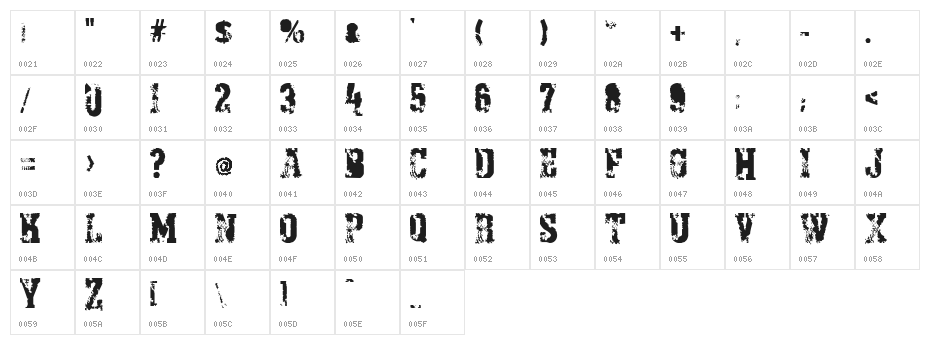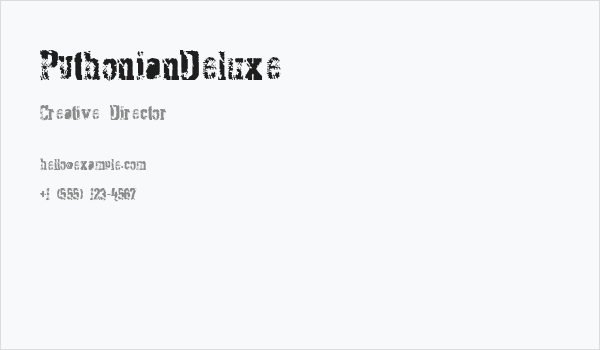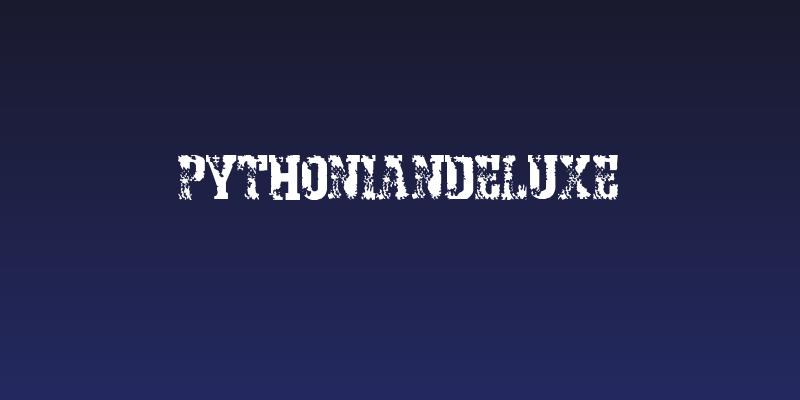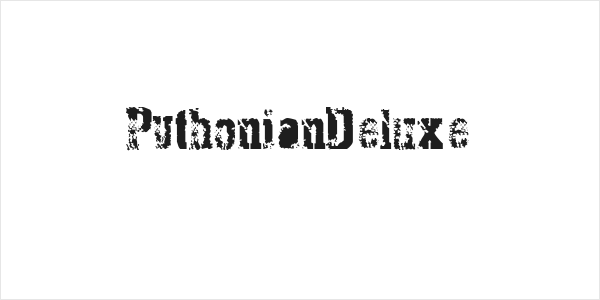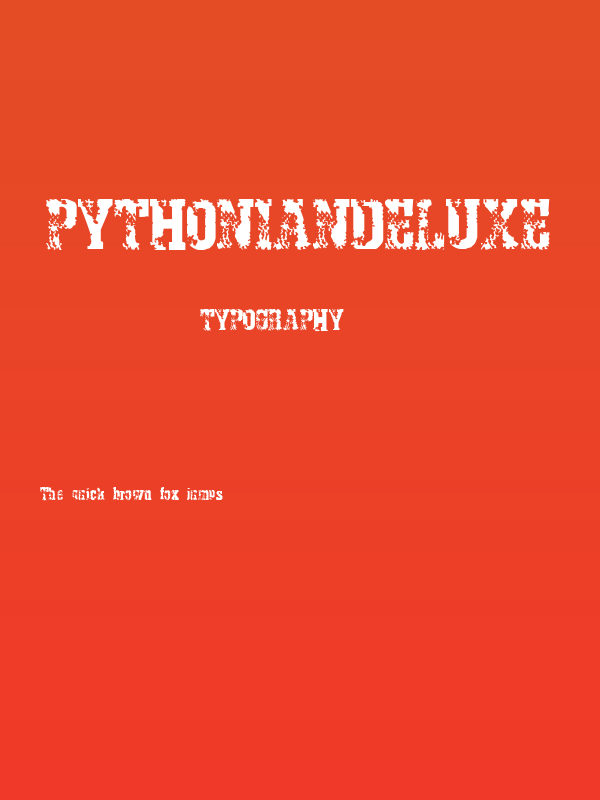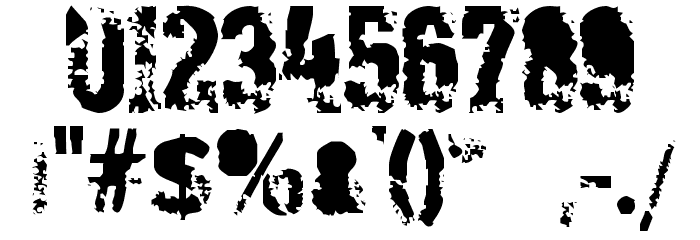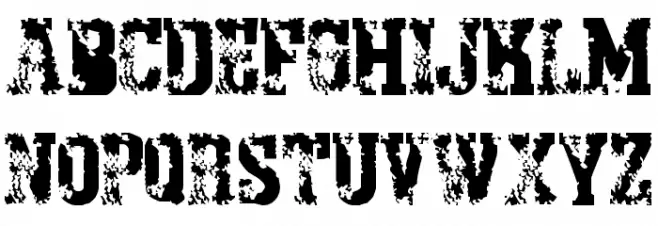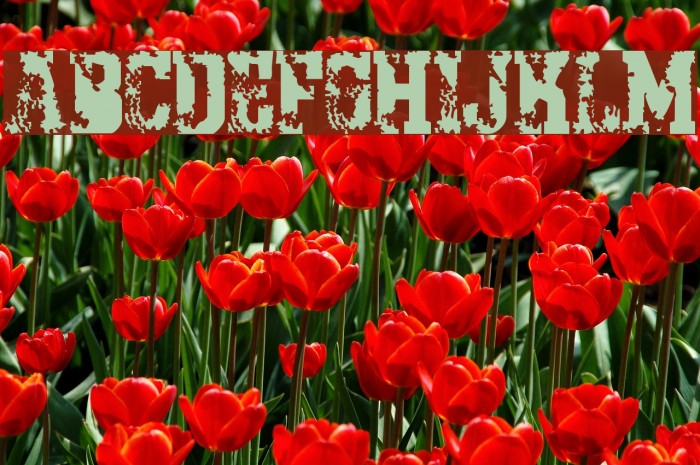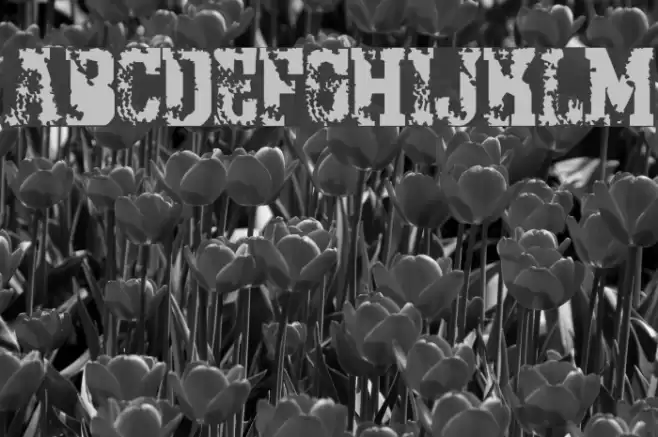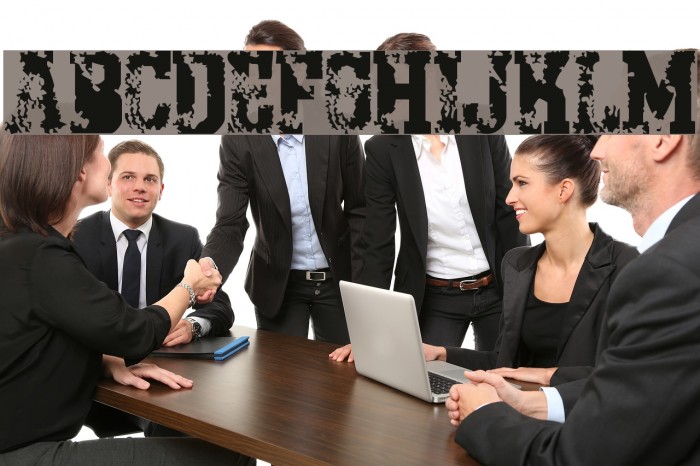
PythonianDeluxe Font
✎ Distorted Eroded
| Style général | Vintage, Grunge |
| Projets proposés | Ideal for posters, album covers, branding for edgy or vintage-themed products, and any design requiring a bold, impactful statement. |